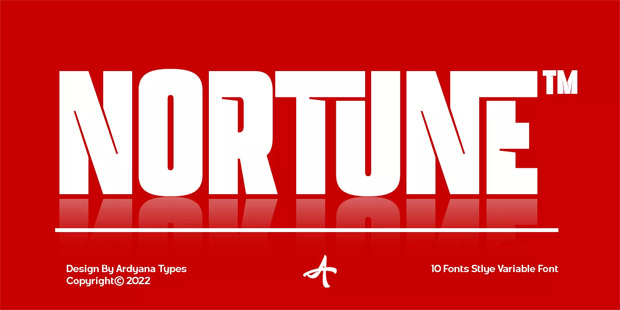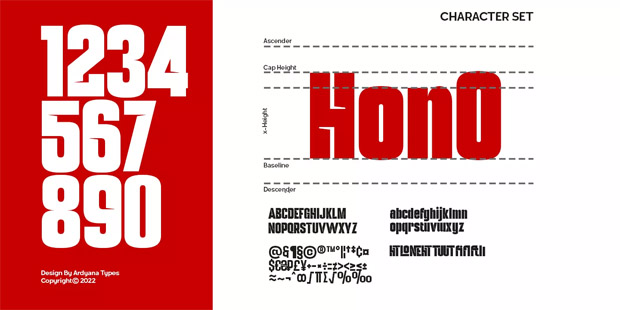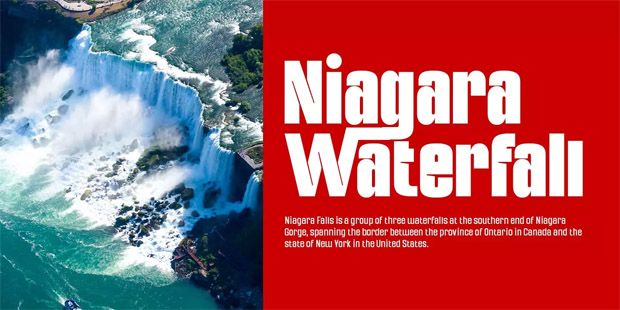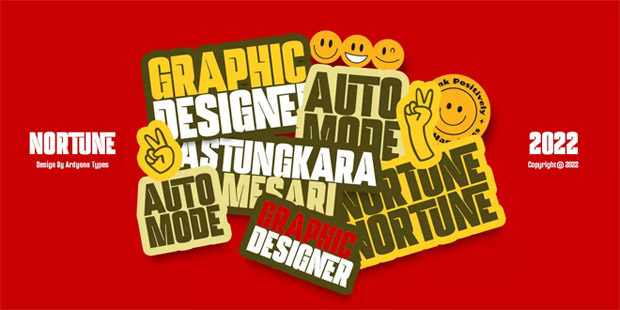
خط نورتن الإنجليزي بالأسلوب العصري الكلاسيكي السميك .. يستوحي خط نورتون تصميمه من مزيج بين الأسلوب العصري والأسلوب الكلاسيكي، مما يمنحه شكلاً ديناميكياً وأنيقاً. يُناسب هذا الخط جميع التصاميم التي تجمع بين الطابع العصري والكلاسيكي، يُعد نورتون مثالياً لمشاريع العلامات التجارية وأغراض التصميم المتنوعة، مثل بطاقات العمل، وبطاقات الأسماء، والإعلانات، والملصقات، وبطاقات الدعوة، والشعارات، والمجلات، والمنتجات الترويجية، والعروض التقديمية، وغيرها.